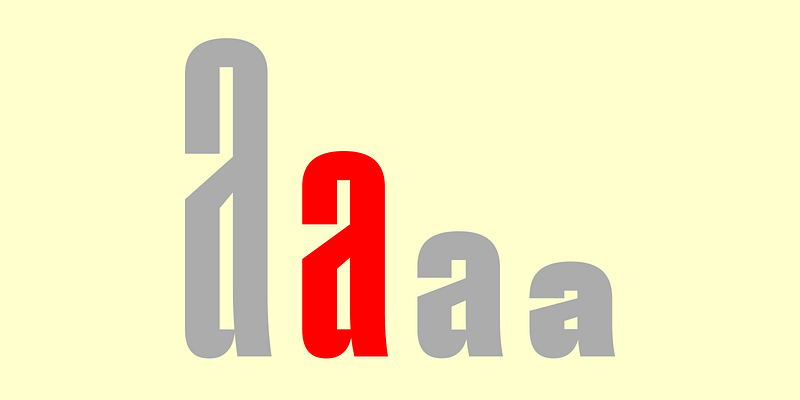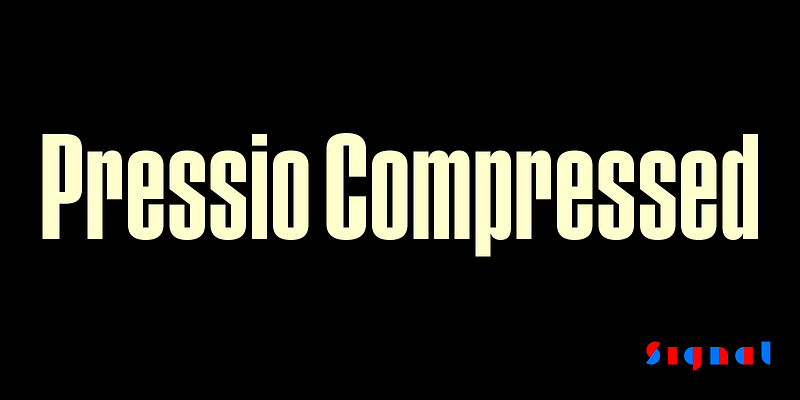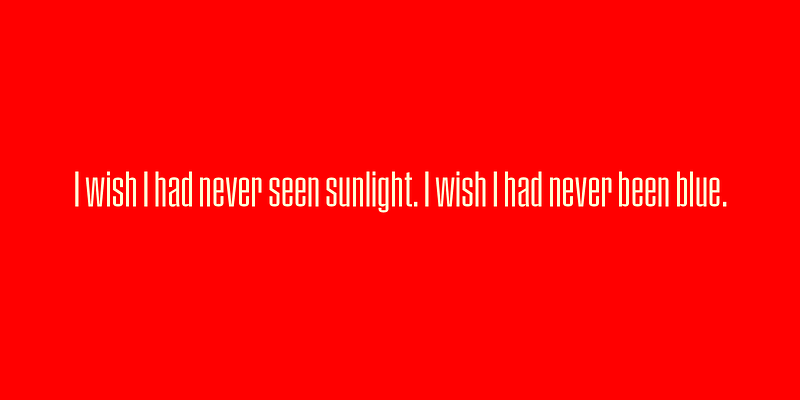
El sistema de tipos Pressio es un estudio sobre cómo hacer las cosas al revés. En primer lugar, comenzamos con el grosor que normalmente se dibuja en último lugar: el negro ultracomprimido. Se aplastó verticalmente en incrementos para hacer los anchos comprimidos, condensados y regulares, y luego se ahuecó como una canoa para producir los grosores más ligeros. 20 estilos en cinco grosores y cuatro anchos proporcionan una amplia gama de expresión. Incluye versiones de ancho completo, condensado, comprimido y extracomprimido.